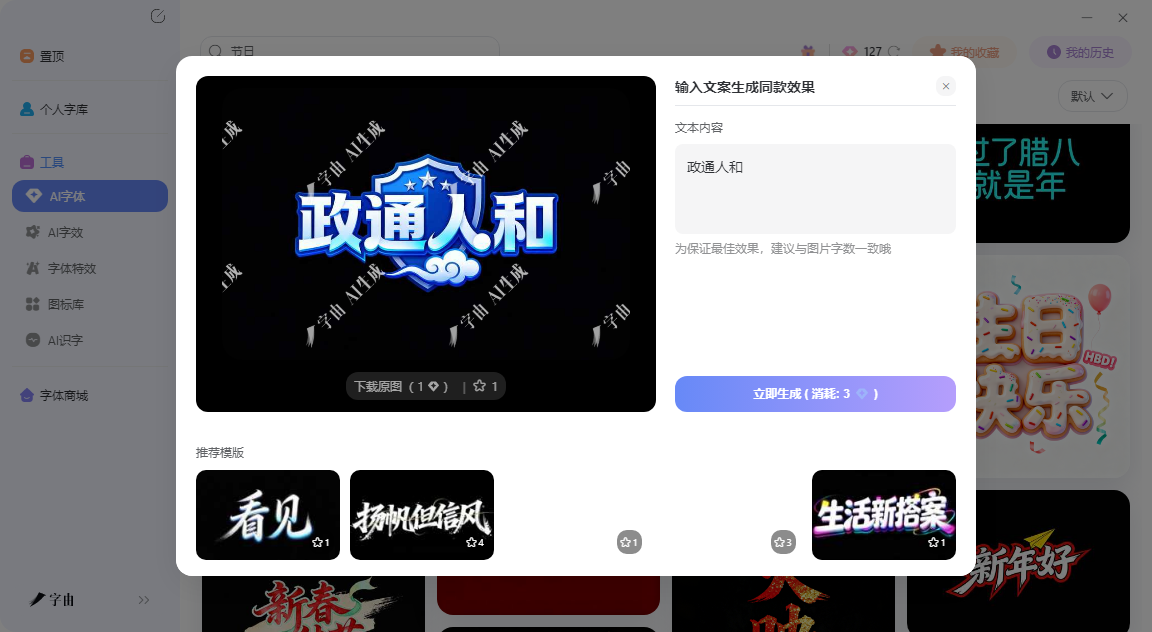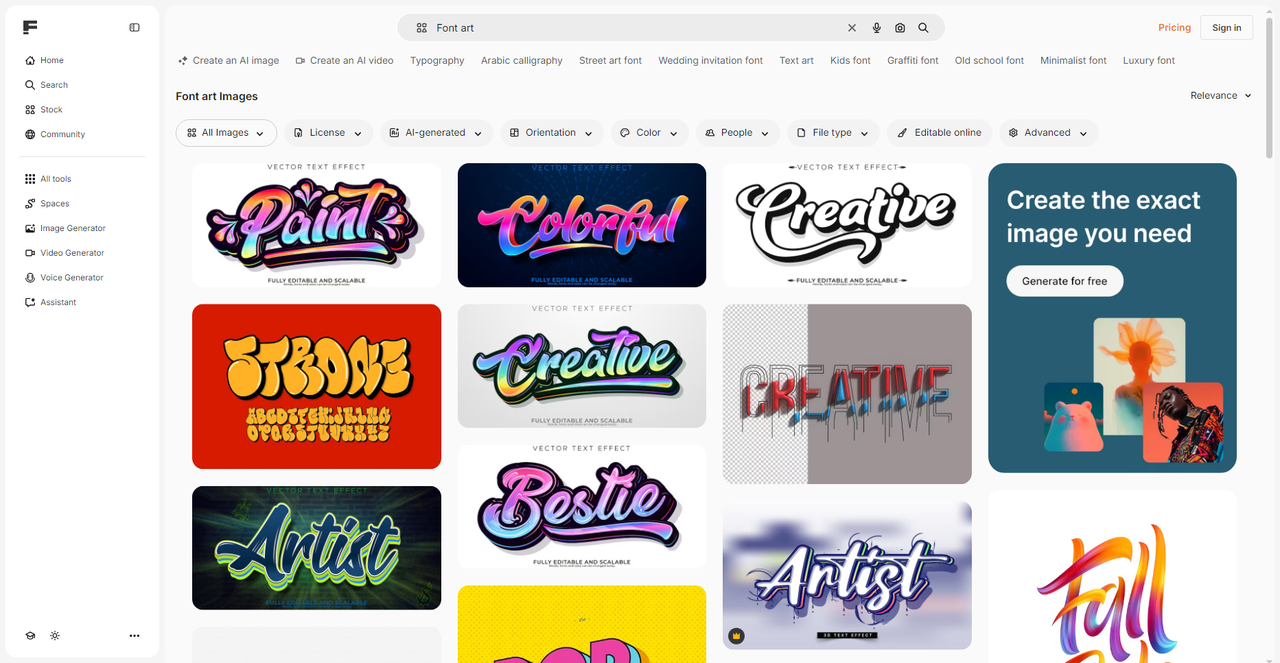
零基础做艺术字:在线工具让你秒变设计大师
现在想做一个海报标题已经不需要自己手动去PS里面设计和调整了,因为现在市面上的很多AI工具已经足够成熟,最起码也能帮助你设计一个艺术字的雏形,实在不满意了可以再自己进行调整,效率高了不止一倍,那么今天我就整理了6个艺术字制作相关的网站,从AI一键生成到矢量素材下载,从免费字体到专业模板,零基础也能上手。
聊艺术字制作,绕不开字由。它和传统做艺术字的方式完全不同——你不需要懂图层样式、混合模式、滤镜参数,甚至不需要知道什么是“内阴影”。打开字由的AI字体功能,400多套现成的艺术字模板摆在你面前,选一个顺眼的就可以直接开始生成了,生成过程甚至用不到一分钟。
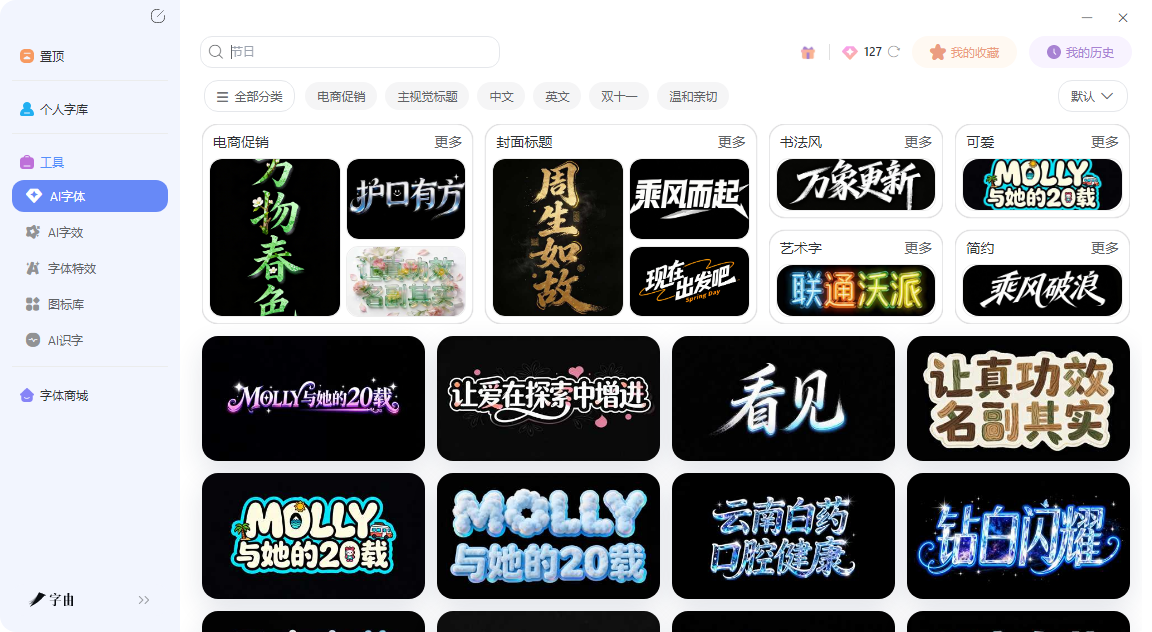
当然这些模板不是随便拼凑的,比如“金属质感”分类下的模板,金属的高光、暗部、拉丝纹理都已经配好了;“霓虹灯”分类下的模板,发光颜色、光晕范围、背景暗度都经过了测试。你不需要知道这些参数怎么调,只需要判断“这个风格适不适合我的项目”。
最主要的是,字由的AI字体页面按场景和风格做了分类。想做国潮风的海报标题,点“国潮风”;想做夜店活动的霓虹灯字,点“霓虹灯”;想做工业风的产品标题,点“金属质感”。每个分类下面有几十款模板,预览图直接展示效果。选中后点“做同款”,输入你的文字,10秒左右生成,下载透明背景的PNG,直接放进海报里。
2、Font Art
第二个网站是Font Art,来自Freepik。它不是让你自己生成艺术字,而是提供已经做好的矢量文字特效素材。截图里展示了“Pencil”“Colorful”“Creative”等多种文字特效的预览图,每款都标注了“Fully editable and scalable”(完全可编辑和可缩放)。这些素材通常以EPS、AI或SVG格式提供。下载后,你可以用Illustrator或Inkscape打开,把文字改成你需要的文案,颜色、大小都可以自由调整。Freepik上有大量免费素材(需要署名),也有付费的高级素材。如果你会一点点矢量软件的基础操作,这种方式比从零开始做特效快得多。适合有一定设计基础、想要更多控制权、但又不想完全自己动手的用户。
3、FontsForYou
第三个网站是FontsForYou。它专门收集艺术字体(Art Fonts),分类下共有190款字体,每款都标注了授权类型和下载次数。比如“Patamon Regular Font”标注“free for personal use”(个人使用免费),下载量7166次。这个站的字体分类很丰富,有Beautiful Fonts、Cheerful Fonts、Military Fonts、Designer Fonts、Famous Fonts、Cool Fonts、Unusual Fonts、Basic Fonts等。你可以按分类浏览,也可以直接搜索字体名称。下载前注意查看授权——大部分是“free for personal use”,商用需要另外确认。如果你需要安装一款艺术字体到电脑上长期使用,FontsForYou是一个不错的资源站。下载后得到TTF或OTF文件,双击安装就能在PS、Word里用了。
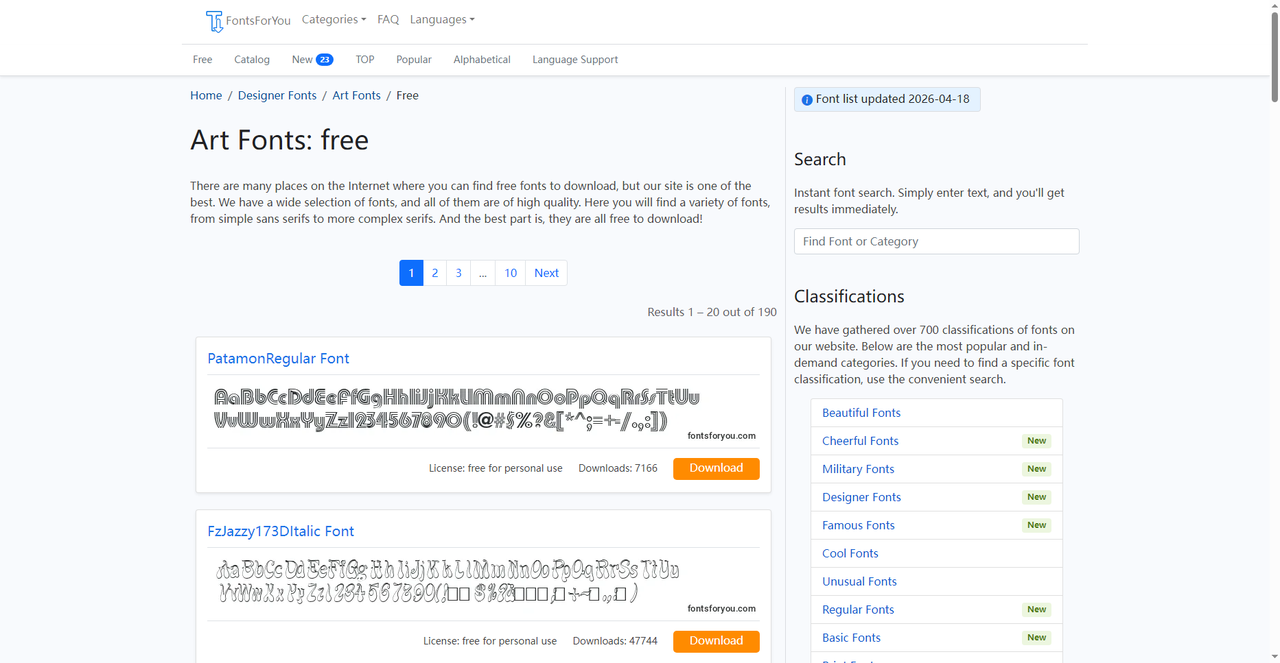
4、FontsIsland
第四个网站是FontsIsland。它的“Art fonts”分类下共有1074款字体,全部免费下载,无需注册。主页展示了Ambassador、ArbatC、Mrs Onion Monsters、Sony [Rus by me]、ArtModernAP、Kelvinch Italic、Kelvinch Bold、Beckett-KanzleiCYRegular等字体,每款都标注了下载次数(从几千到几十万不等)。这个站最大的优势是免费且无需注册。如果你需要下载大量艺术字体用于个人项目,FontsIsland是一个很实在的资源站。不过授权大多是“个人免费使用”,商用前建议仔细查看每个字体的授权说明。
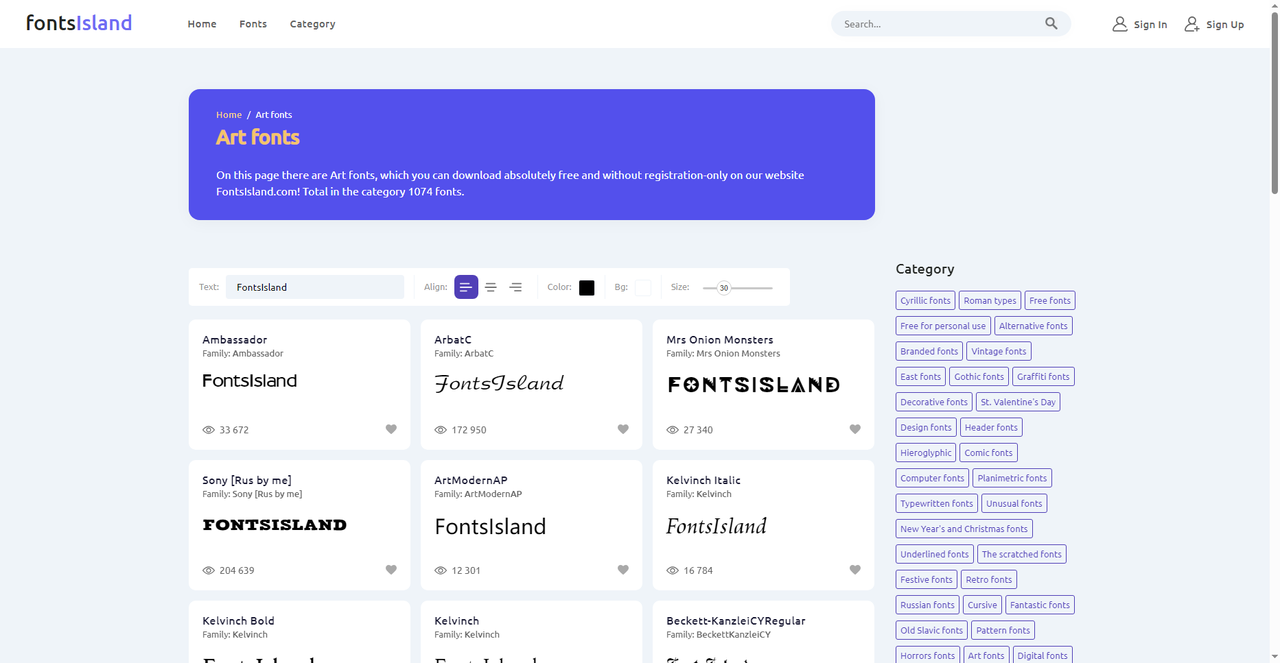
5、Art Fonts
第五个网站是Art Fonts,来自Envato Elements。这是一个付费订阅制的设计资源平台,但它的字体预览页面展示了大量高品质的艺术字体。里有“ART OF SPEAK”“ART BRUSH”“EL:DIÉ”“Art School Dropout”“Classic Serif”等预览,每款都有详细的风格描述。Envato Elements的字体质量明显高于一般免费站。它们大多是专业字体设计师的作品,涵盖衬线体、无衬线体、手写体、装饰体等。如果你预算允许(月费约16.5美元),可以无限下载平台上的所有字体、模板、图片等资源。对于经常做设计的人来说,订阅制的性价比远高于单款购买。即使不订阅,你也可以在这个页面上浏览字体预览,作为灵感参考。看到喜欢的字体风格,再去找类似的免费替代品。
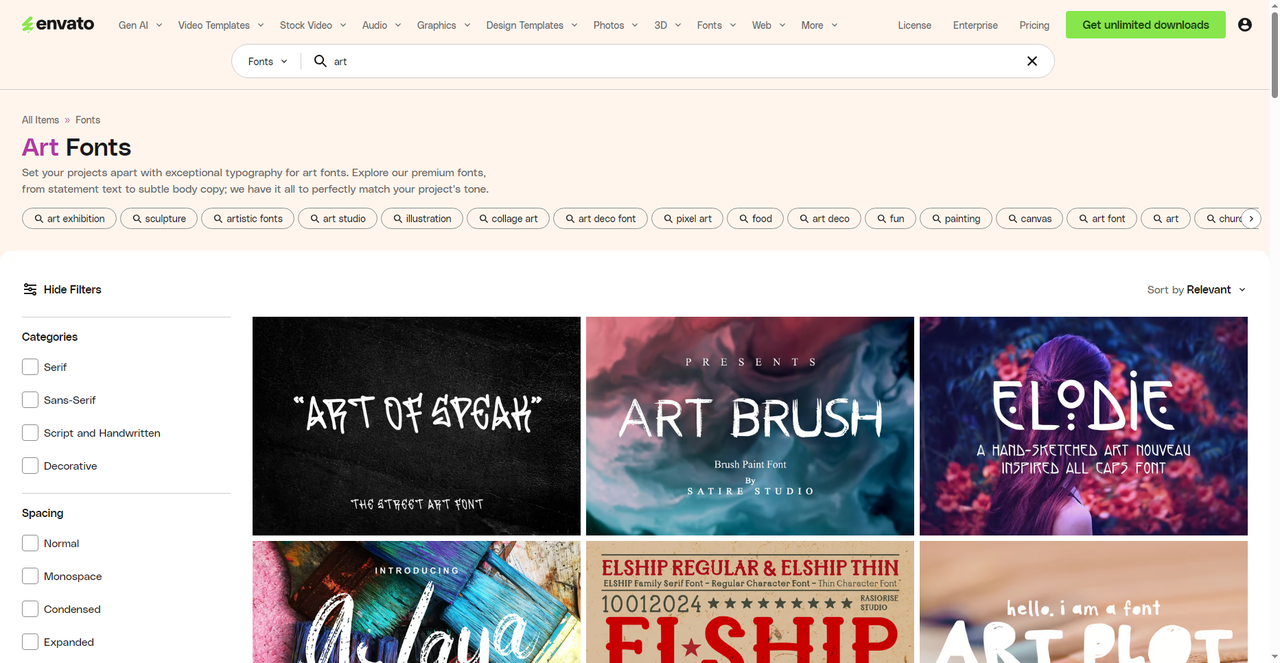
6、ArtFont
第六个工具是ArtFont。它和字由的AI字体类似,提供200多种专业模板,覆盖书法、涂鸦、霓虹、极简、复古等风格。输入文字,选择模板,点生成,10秒左右出图,支持2K/4K高清导出。ArtFont的亮点是模板更新频率高——“New styles added weekly”(每周新增样式)。你也可以浏览其他用户创作的120万多种字体效果,从中寻找灵感。ArtFont每天登录送免费积分,新手有20免费积分。如果你需要生成高清印刷级艺术字,ArtFont是一个不错的备选。不过它在中文模板的支持上可能不如字由丰富,更适合英文项目。